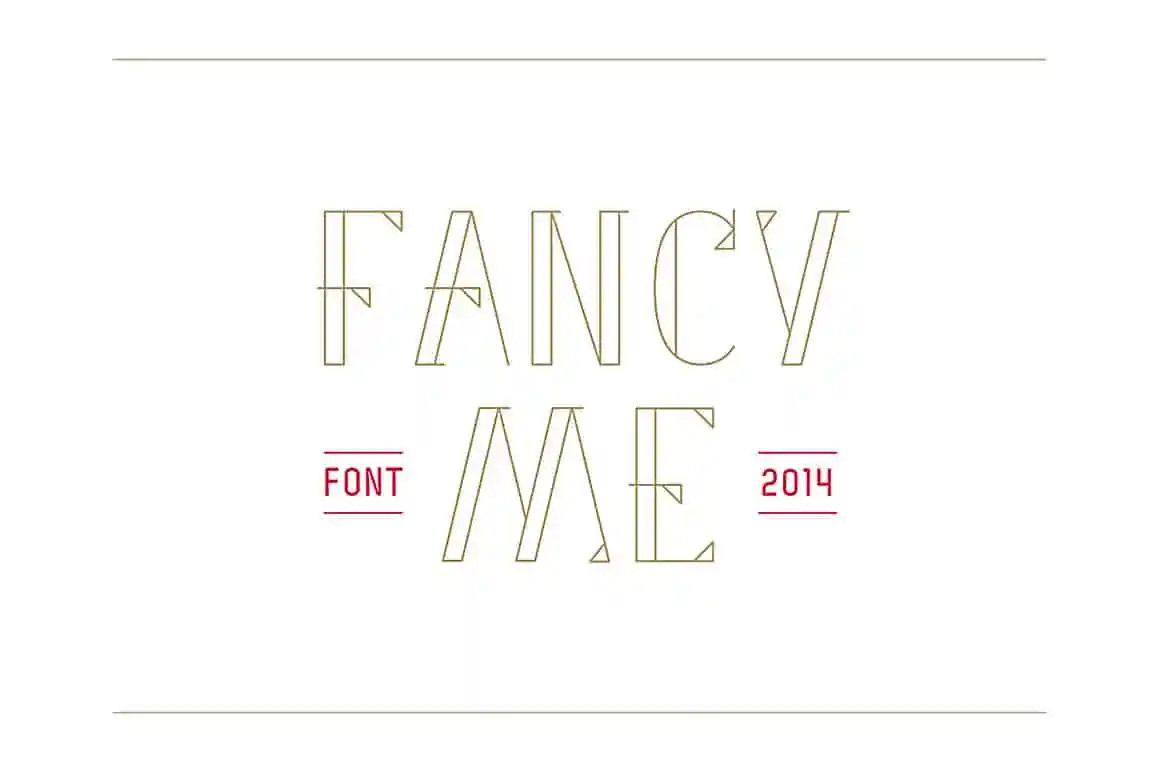
A font FancyMe é uma criação do designer Hamilton que traz uma atmosfera fresca e criativa para qualquer projeto. Inspirada pela versão do Marie-Michelle Dupuis, esta custom font tem um estilo único de modernidade e limpeza, perfeita para seus próximos projetos decorativos. Não importa se você está trabalhando em cartazes, designs digitais ou até mesmo artesanato, o seu texto ficará imediatamente atraente com esta font. Descarregue-a agora e comece a experimentá-la nos seus projetos. Divirta-se 😉